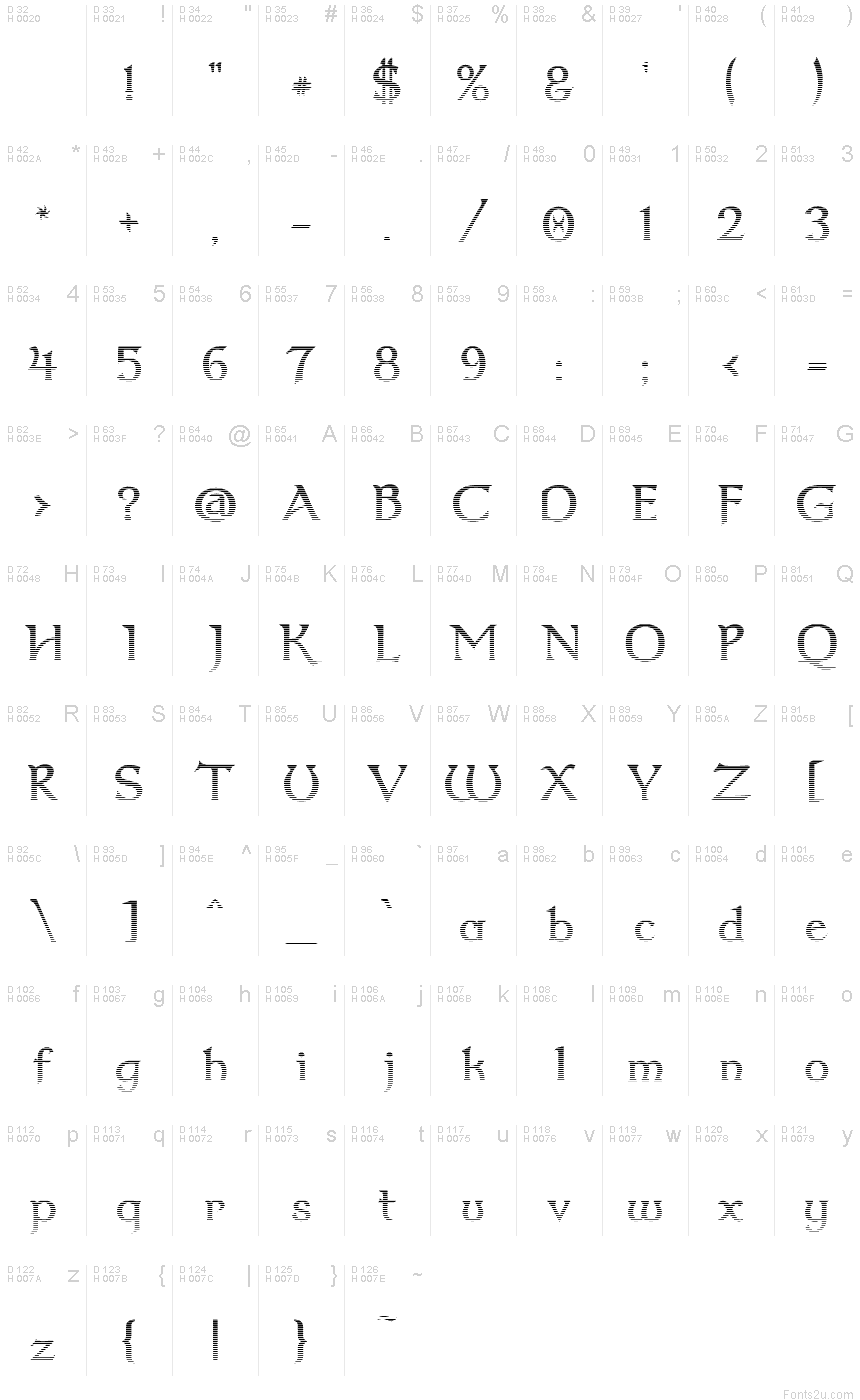
Dumbledor 2 Cut Up
Dumbledor 2 Cut Up od GeM/FF to darmowy, ozdobny krój pisma, który przecina klasyczne szeryfowe kształty na wąskie, poziome pasy. Litery sprawiają wrażenie, jakby migotały podczas skanowania: są wyraziste, równomiernie prążkowane i lekko hipnotyzujące. Mimo to zachowują strukturę zapewniającą czytelność, jednocześnie oferując ciekawy, „glitchowy” charakter. Pismo ma silny, poziomy rytm, który prowadzi wzrok wzdłuż linii, nadając nagłówkom poczucie ruchu i cyfrowego szumu bez zbędnego chaosu.
Dzięki Dumbledor 2 Cut Up nadasz plakatom, okładkom sci-fi, eksperymentalnym logotypom, ulotkom, napisom w wideo i wyrazistym grafikom do mediów społecznościowych odważny, filmowy klimat. Ten darmowy font najlepiej wygląda w dużym rozmiarze, gdzie cięte pasy mogą „oddychać”, tworząc wibrującą teksturę przypominającą obraz na ekranie. W przypadku tekstu głównego zestaw go z prostym, lekkim krojem bezszeryfowym, aby wycięte pasy pozostały na pierwszym planie.